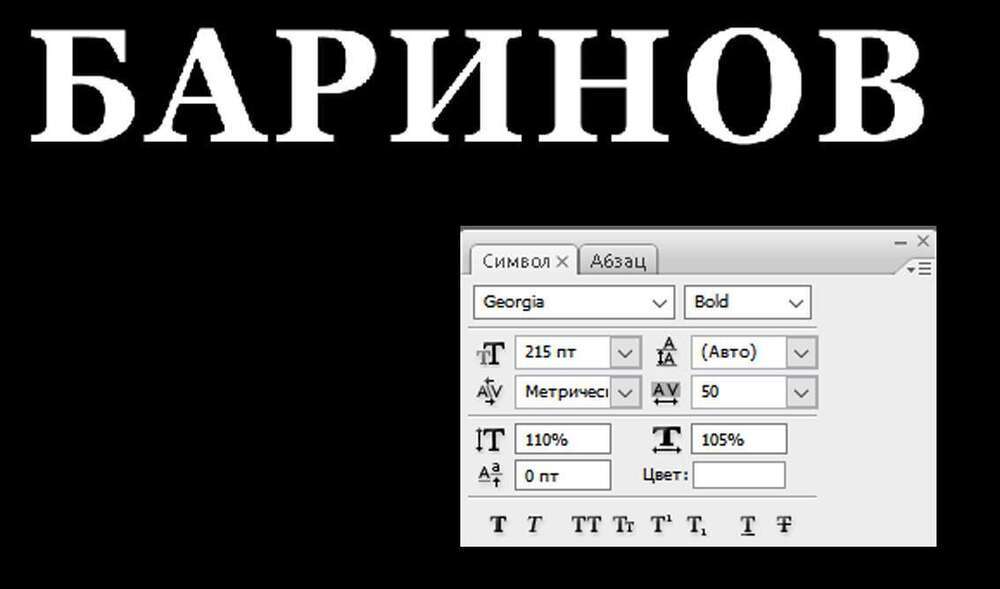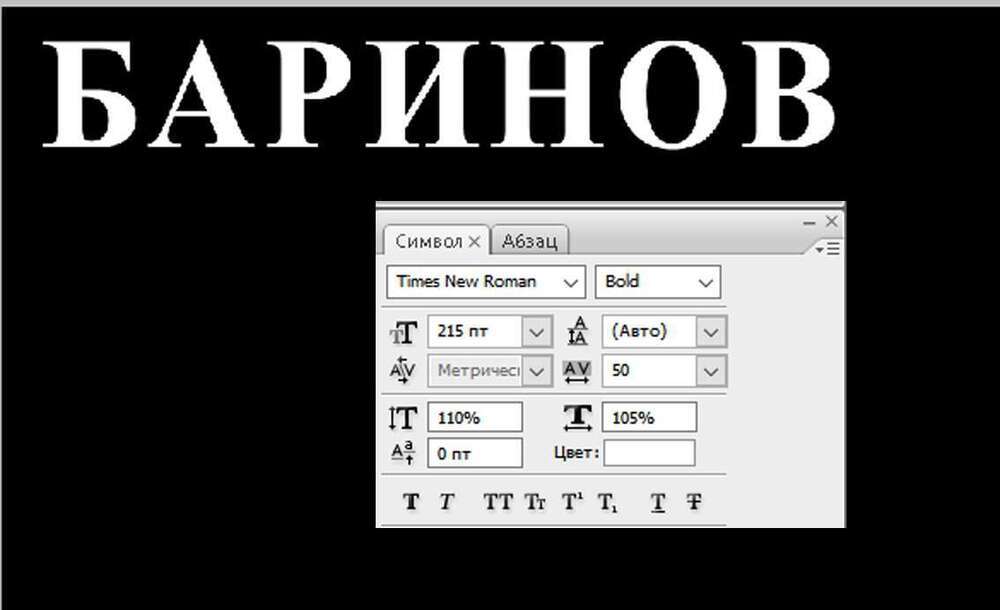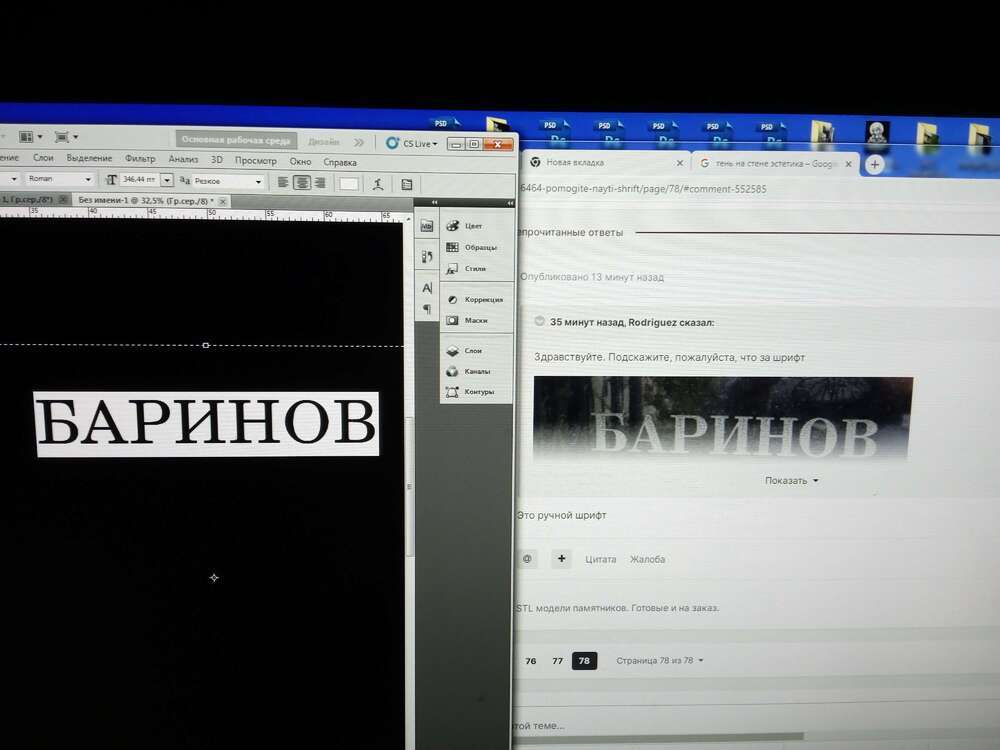
Rodriguez Опубликовано 22 января, 2023 Здравствуйте. Подскажите, пожалуйста, что за шрифт
Денис Давыдов Опубликовано 22 января, 2023 22 минуты назад, Rodriguez сказал: Здравствуйте. Подскажите, пожалуйста, что за шрифт Это ручной шрифт
Мойша Степан Опубликовано 22 января, 2023 @Rodriguez , ставь ТАЙМС (Bold) и будет тебе счастье. Почти не отличается. А можешь вот этот поставить: 3
Мойша Степан Опубликовано 4 февраля, 2023 @ПавелСерп , я в таком случае выбираю буквы одинаковые в латинице и кириллице: А, Е, Т, М, К,Х, Р, О, С. Находит очень хорошо. 1
perez Опубликовано 25 февраля, 2023 если кто знает, подскажите пожалуйста что за шрифт
"Девчонка" Опубликовано 3 марта, 2023 @Смешарик Izhitsa или Izhitsa Cyrillic. Думаю разницы там нет, ну или незначительная. 1
puzhoks Опубликовано 6 марта, 2023 (изменено) помогите найти Изменено 6 марта, 2023 пользователем puzhoks
Soaring man Опубликовано 6 марта, 2023 31 минуту назад, puzhoks сказал: помогите найти сложно будет вам найти шрифт, который чертили вручную Можно близкие к нему поискать. Но точно такой не найдете 1 1
"Девчонка" Опубликовано 7 марта, 2023 @puzhoks a_MachinaOrto посмотрите 1 1